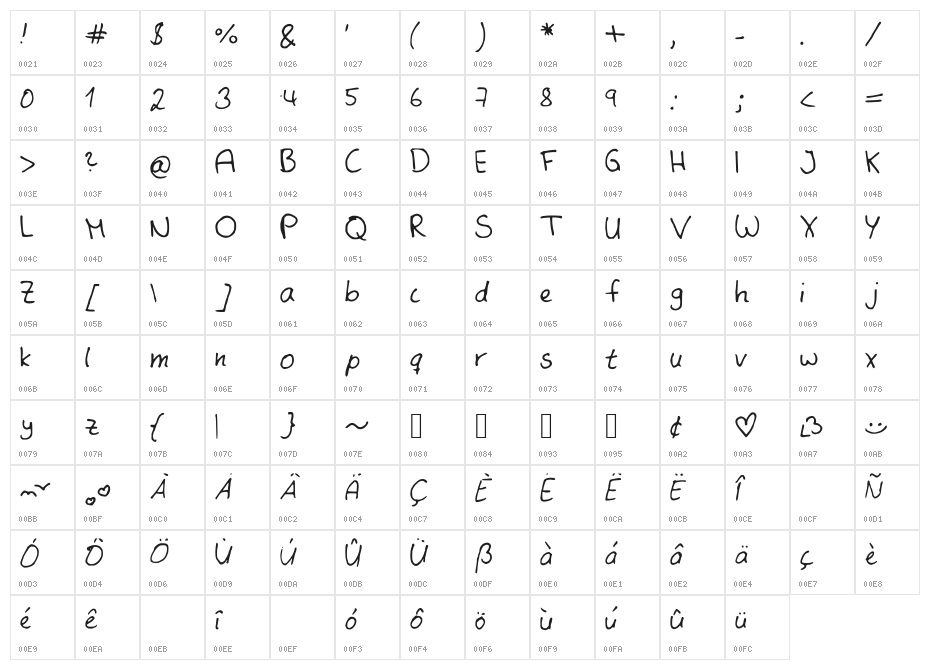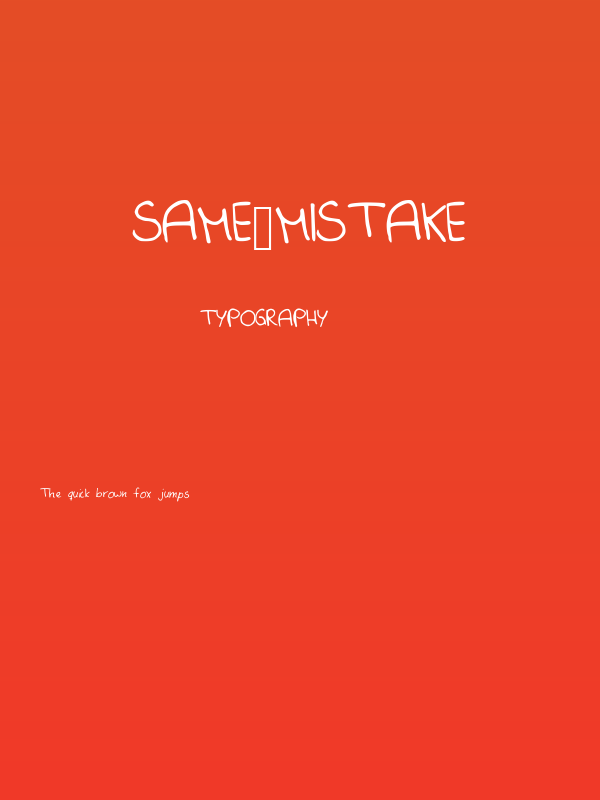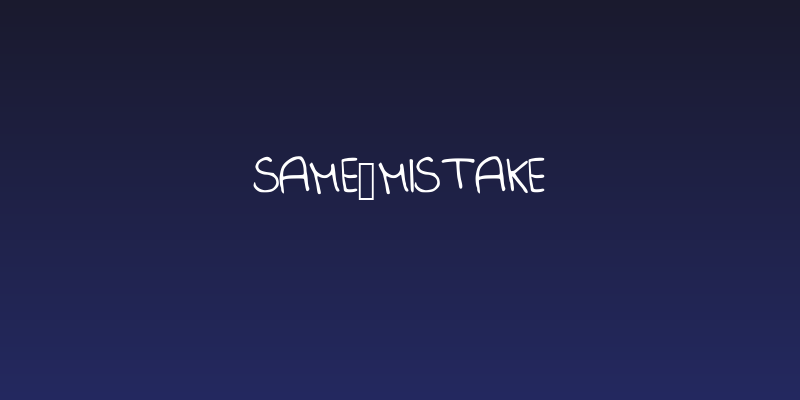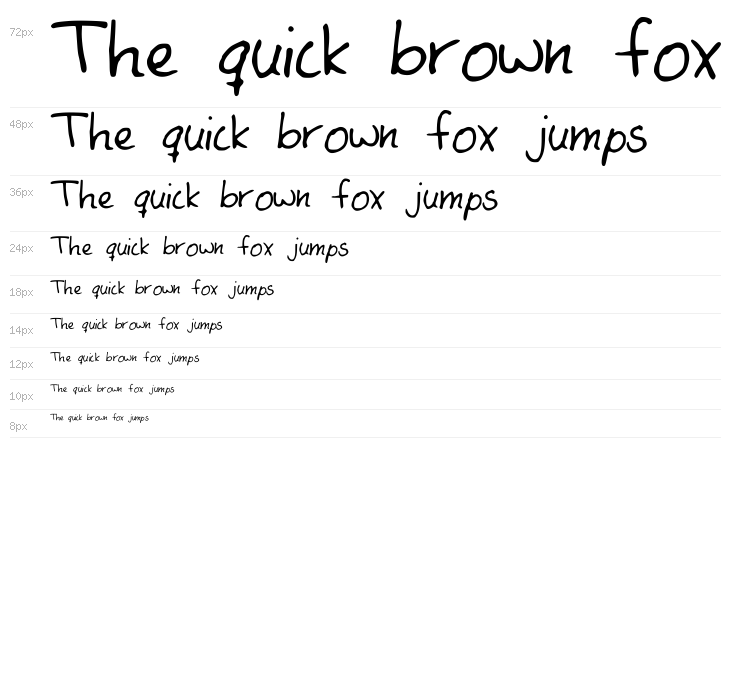
Same_Mistake Font
| Gesamtstil | Casual |
| Anwendungsfall | Logos, Headlines, Informal text |
| Vorgeschlagene Projekte | Ideal for greeting cards, personal notes, informal invitations, children's books, and creative projects that require a friendly and approachable feel. |